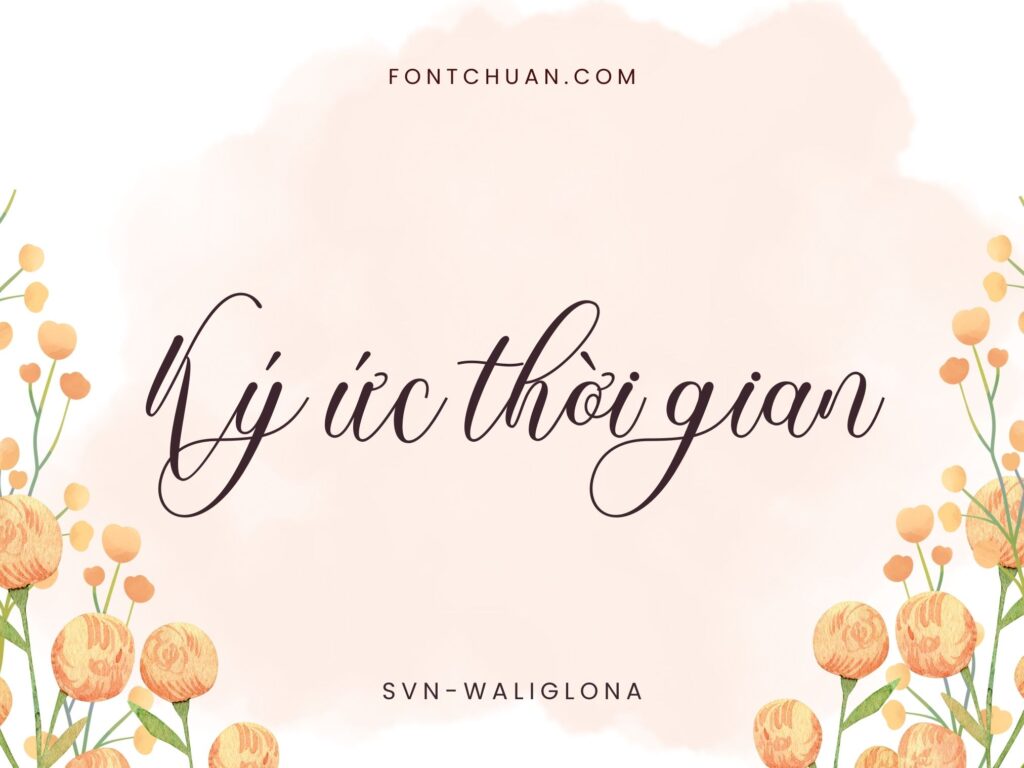
Font SVN Waliglona Việt Hóa
Tác giả Font: Ikhsan Maulana
Font SVN Waliglona là phiên bản Việt hóa của kiểu chữ Waliglona, được thực hiện bởi Styleno.1 Fonts. Waliglona là một Font Decorative viết tay thanh lịch và uyển chuyển, nổi bật với các đường nét mượt mà và các ký tự thay thế tuyệt đẹp. Font này được mã hóa PUA, cho phép truy cập dễ dàng vào tất cả các glyphs và swashes, mang đến sự đa dạng trong thiết kế.
SVN Waliglona lý tưởng cho các dự án thiết kế yêu cầu sự tinh tế và cá nhân hóa, như thiệp mời, logo, tiêu đề và các ấn phẩm truyền thông. Các ngành nghề như thiệp cưới, ẩm thực và spa có thể tận dụng font này để tạo điểm nhấn trong thiết kế. Ngoài ra, font cũng thích hợp cho các sự kiện như Tết, Valentine, Sinh nhật và các lễ hội khác.